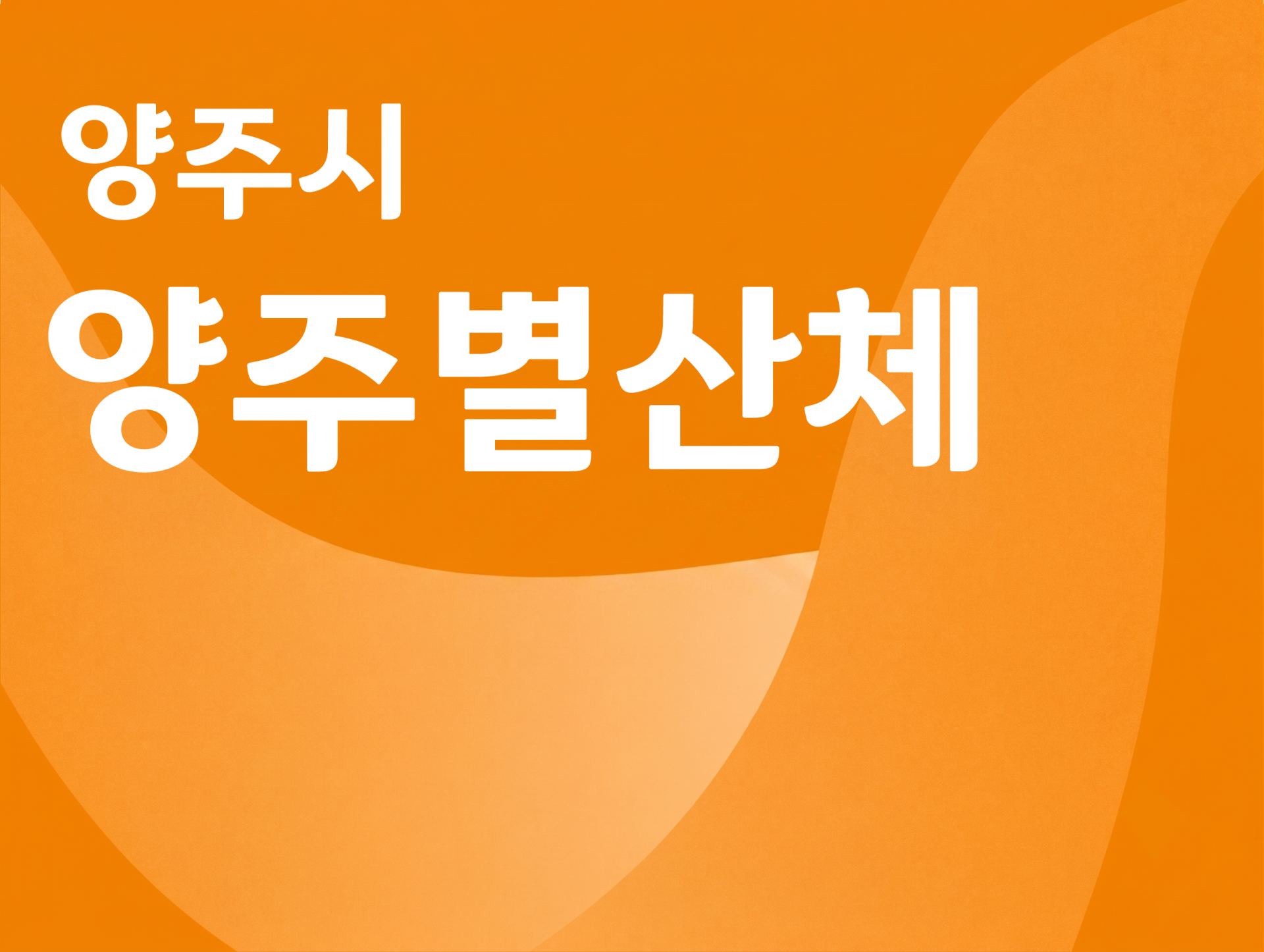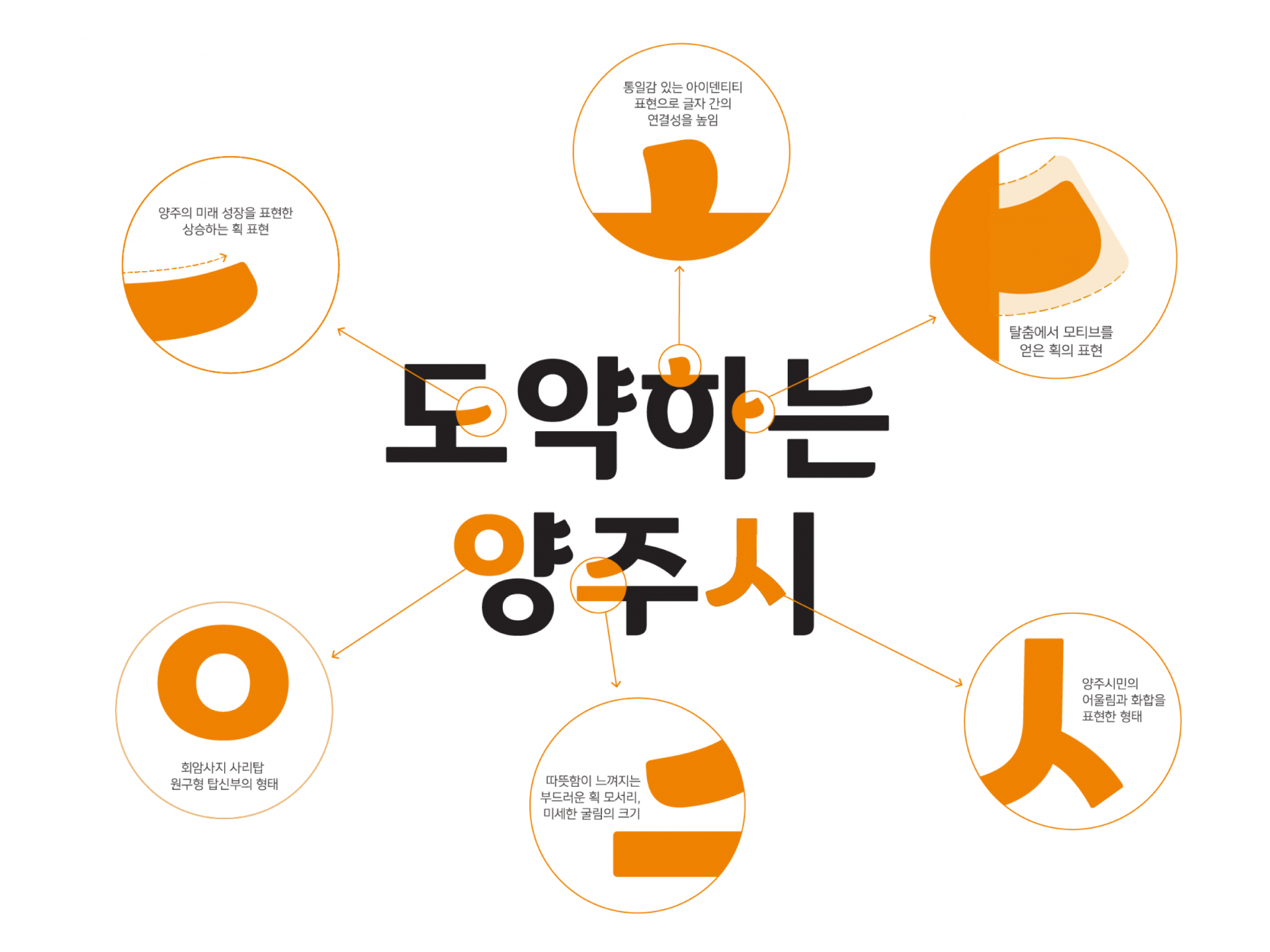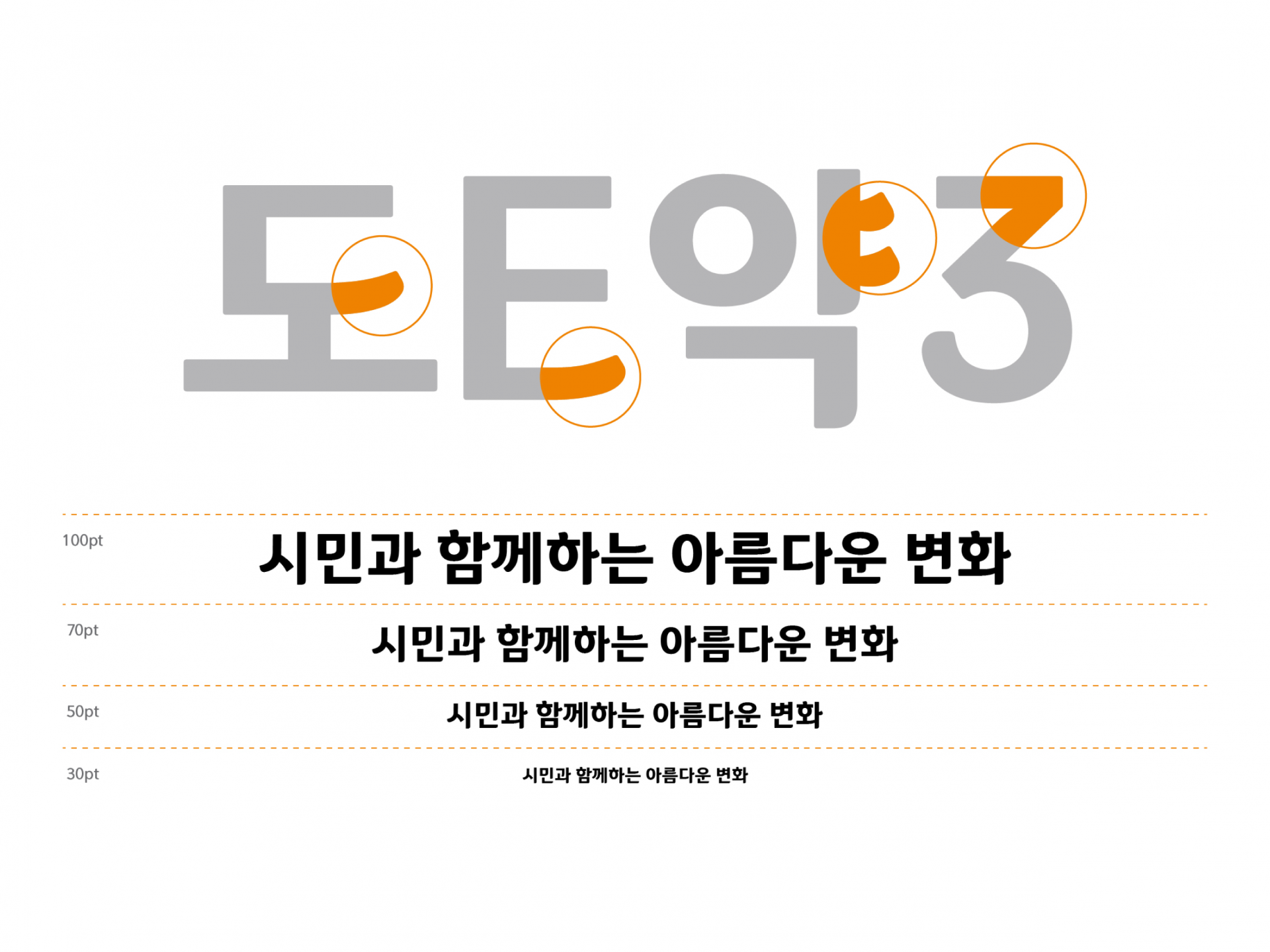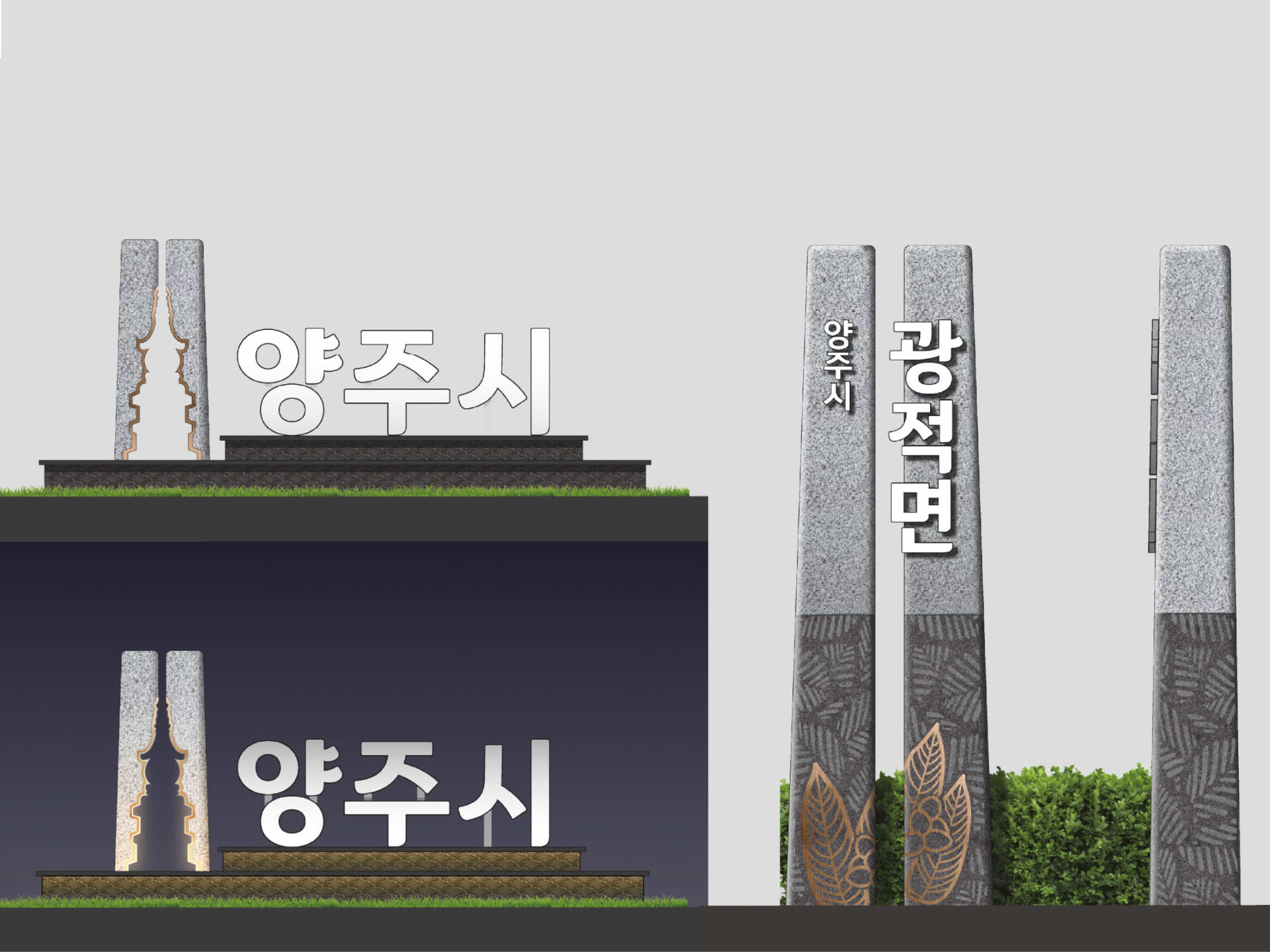
양주시 [양주별산체]
양주시 지역상징물 전용서체는 과거와 미래를 이어주는 현대적 관점으로 제작되었다. 양주시의 600년의 유구한 역사와 양주시를 대표하는 멋과 흥이 넘치는 '별산대놀이' 그리고 양주시의 새로운 비전과 정체성 확립을 위한 잠재적 미래를 담아내었다. 지역의 상징물에 사용되는 기능성을 우선으로 한 사용중심의 서체로 남녀노소 모두를 배려하는 유니버설(universal) 디자인 개념을 담아 가독성과 시인성을 강화하였다.